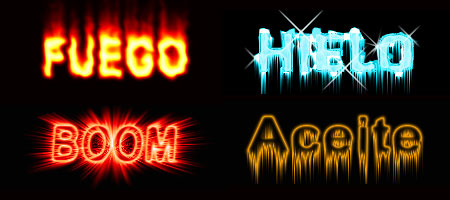
Photoshop tiene infinidad de trucos rápidos para lograr algunos efectos vistosos. Trataré de irlos incorporando poco a poco según recuerde algunos y otros que pueda conseguir; aquí cuatro muy solicitados: Tipografía en fuego, hielo, explosión y aceite.